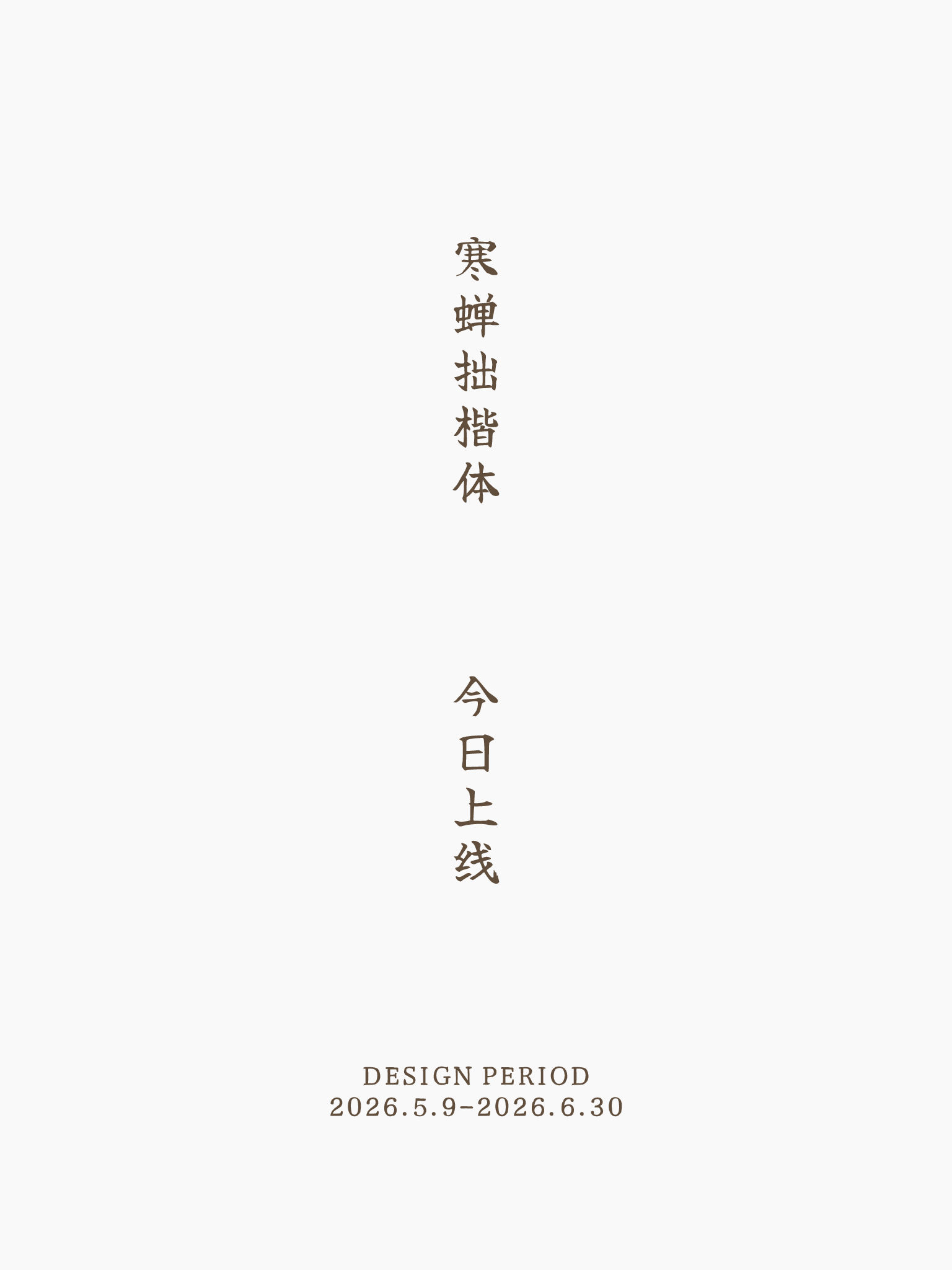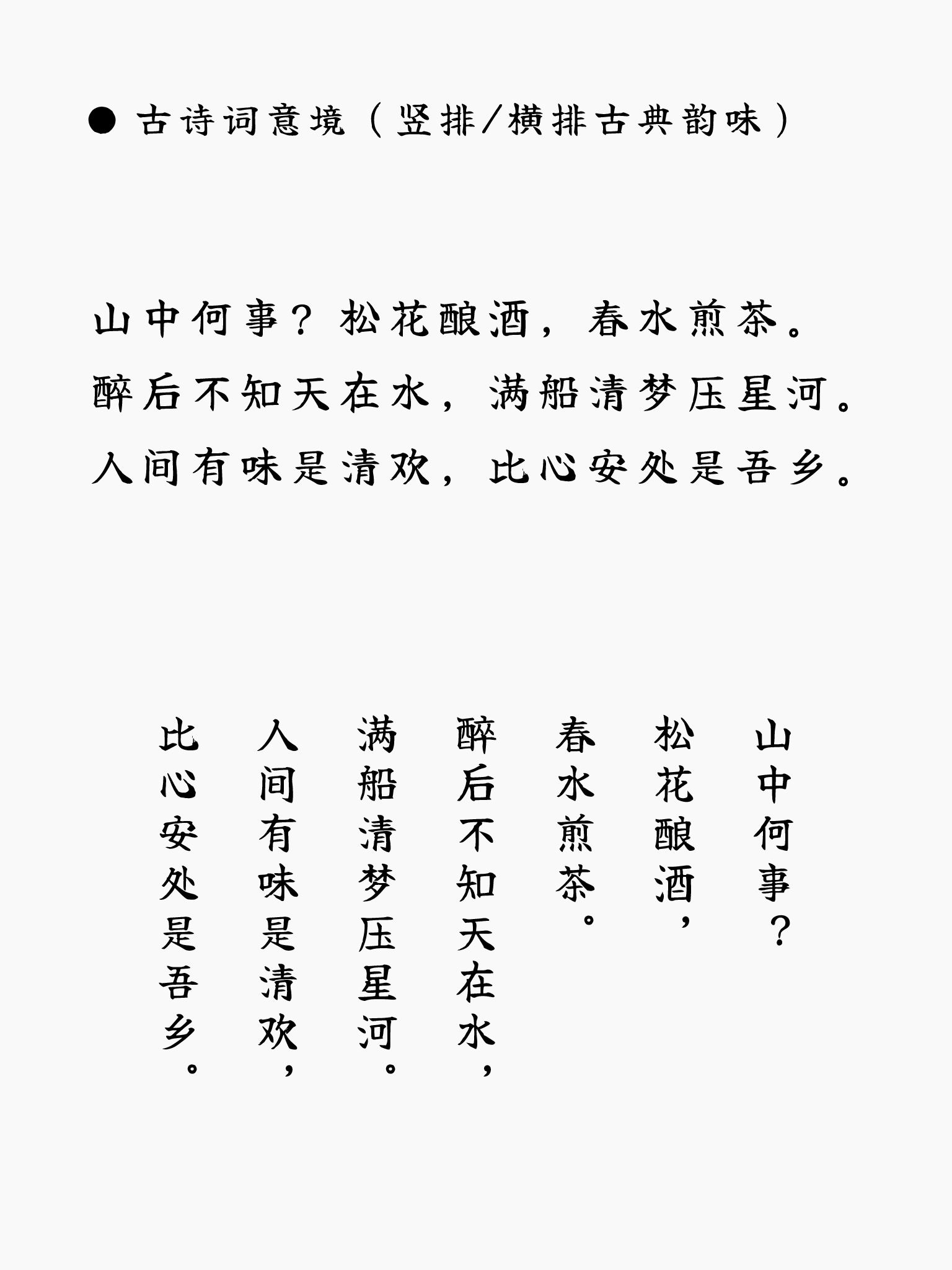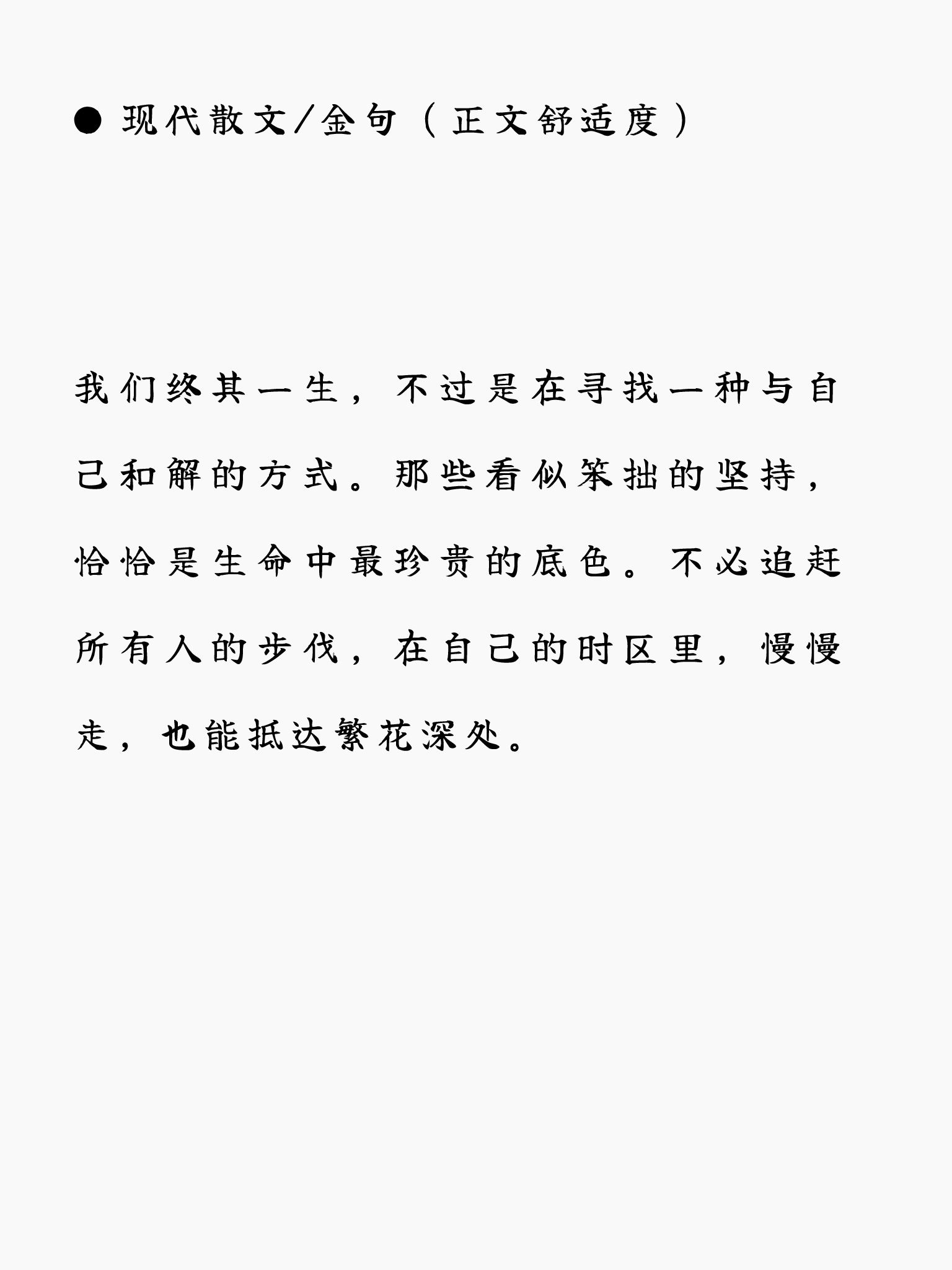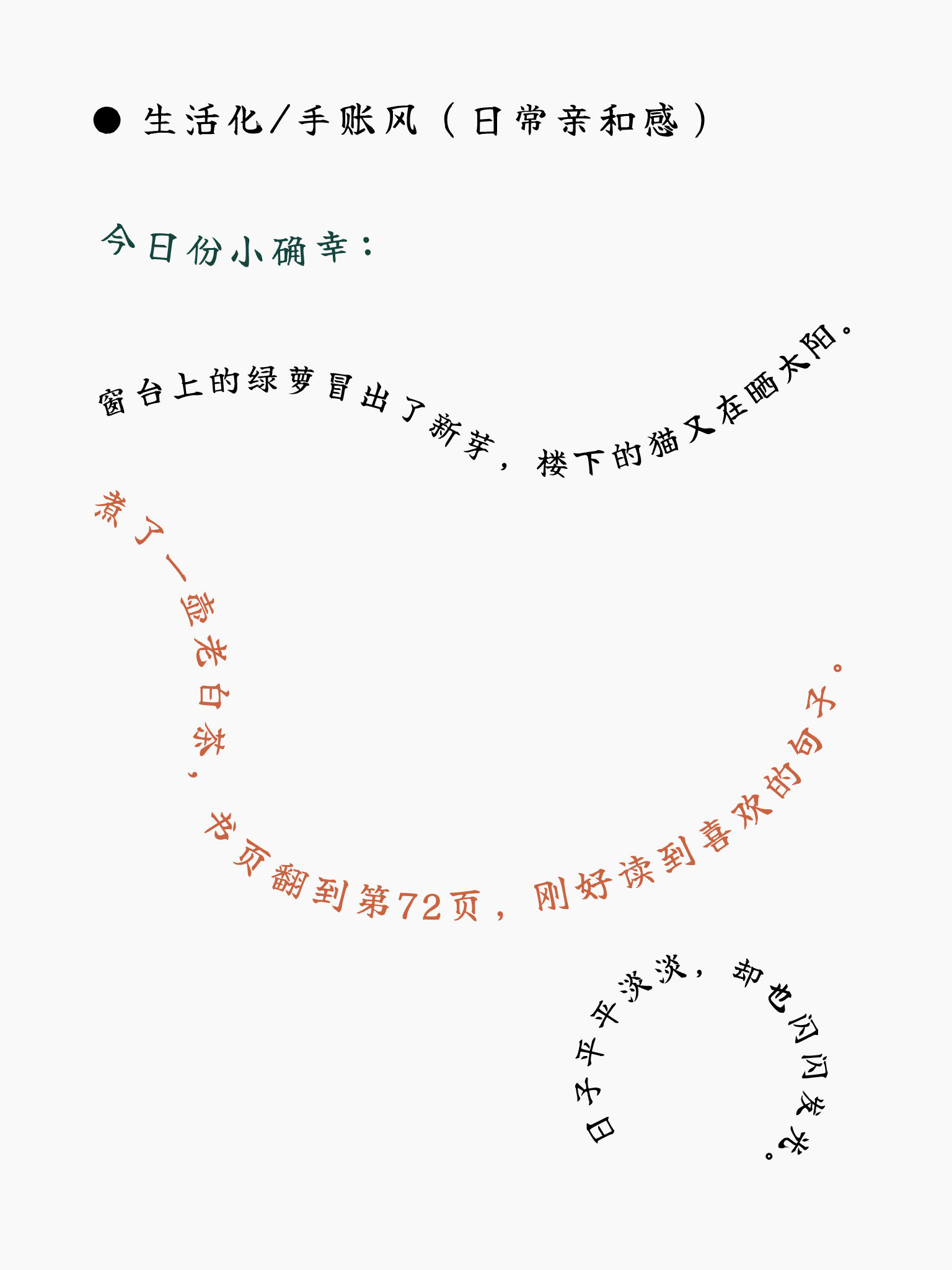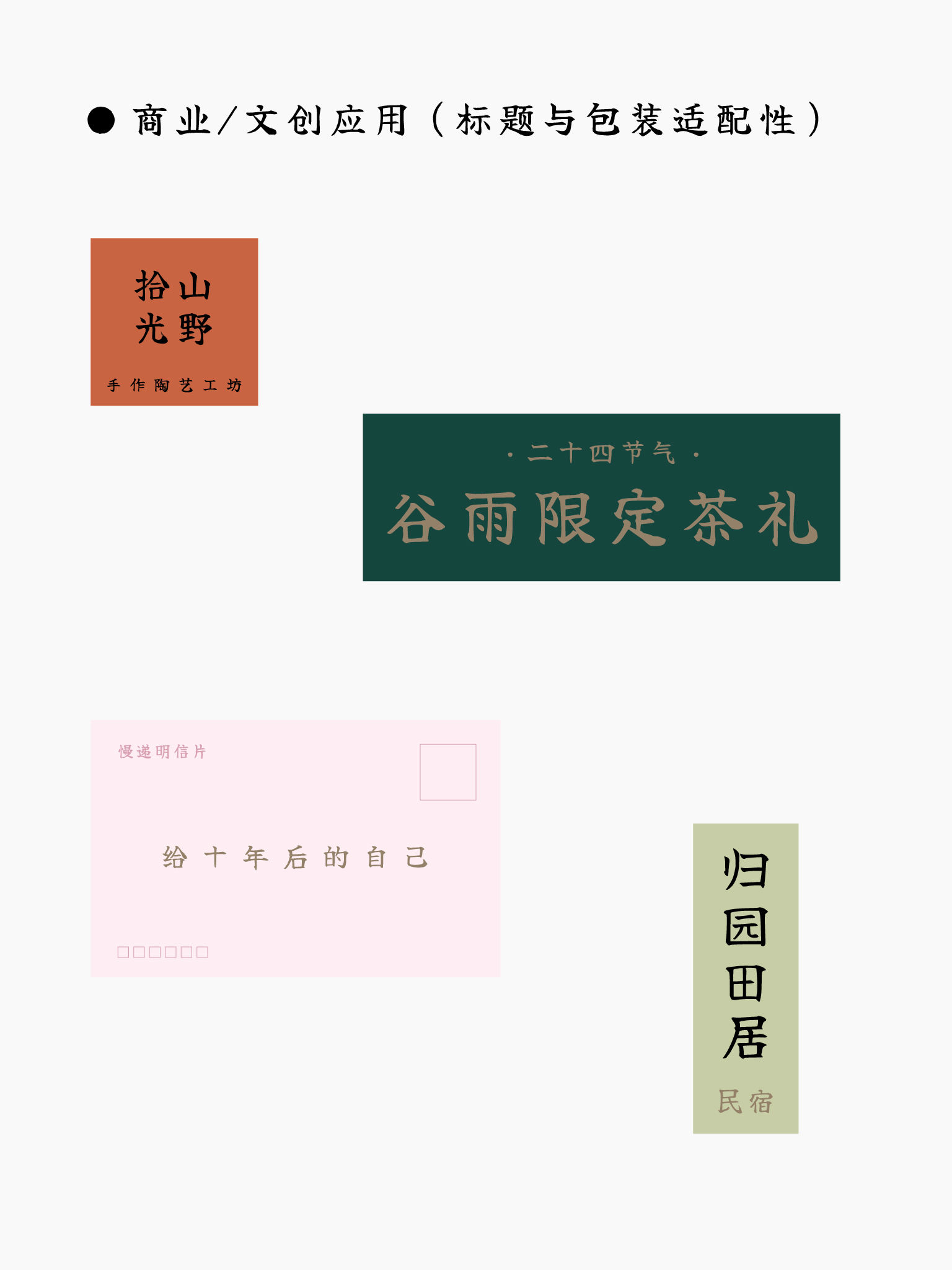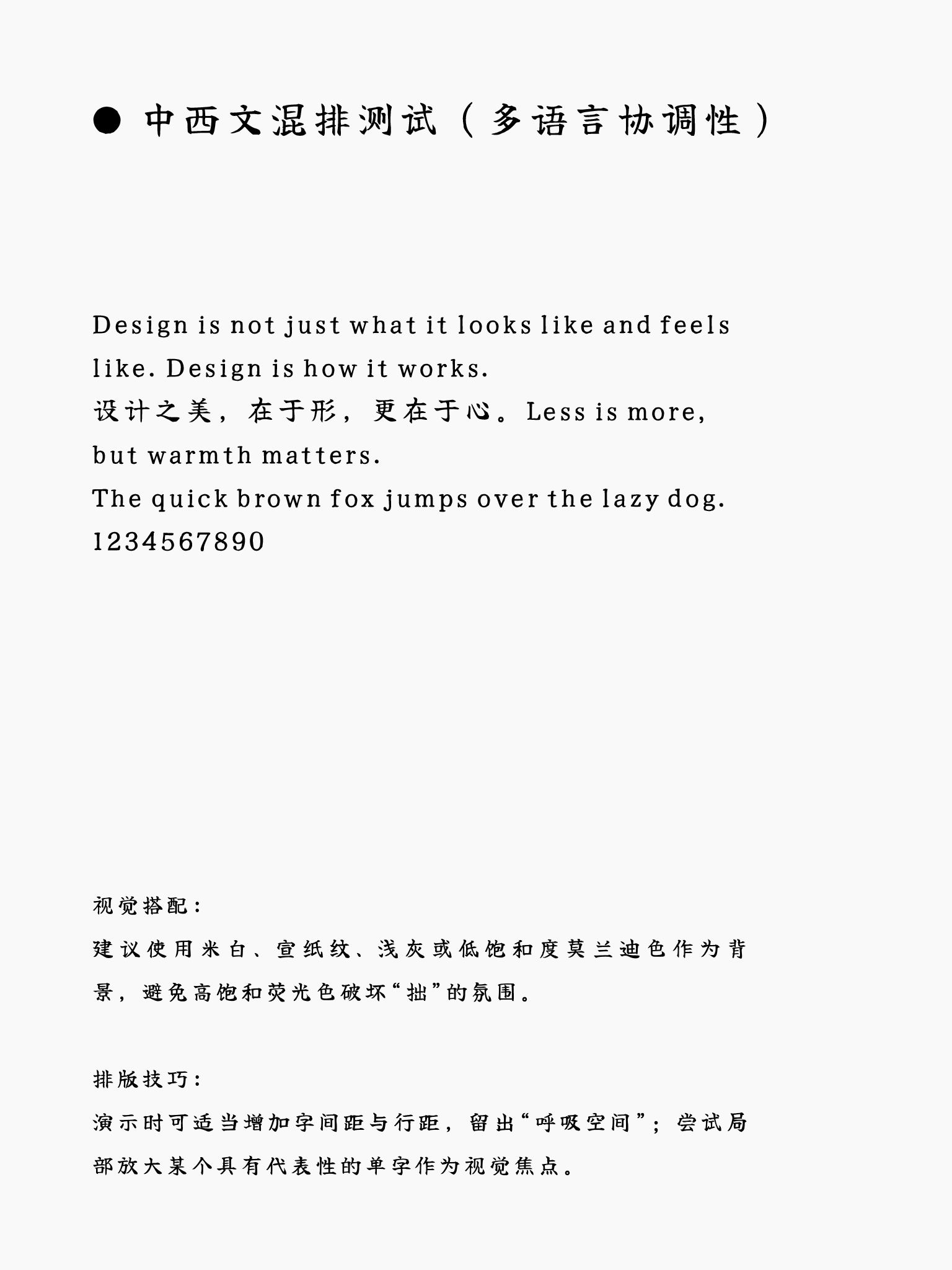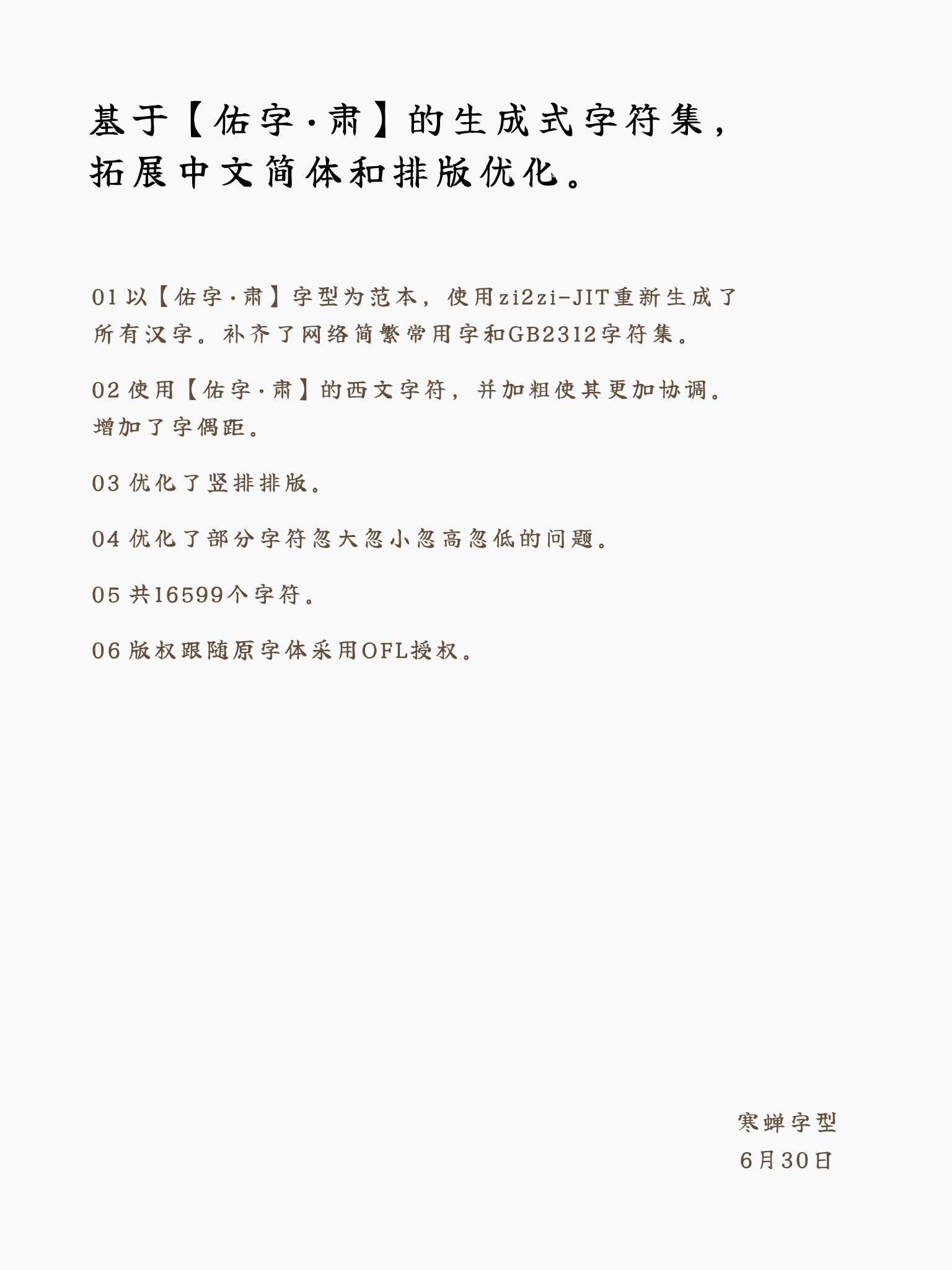
寒蝉拙楷体是一个基于机器学习技术开发的补简字体项目,通过zi2zi-JIT框架生成。该项目旨在扩展和补充特定字体在简体中文字符集方面的覆盖,同时保持其原有的书法风格与美学特征。zi2zi-JIT是一种基于深度学习的字体生成工具,能够有效学习原字体的笔画结构、形态特征以及整体排版风格,进而生成一致且高质量的补全字符。
原字体 Yuji Syuku(佑字 肃)是一款具有传统美感的日文字体,其设计融合了古典书法元素与现代排版需求,尤其在笔画细节和结构平衡上表现突出。为了保持风格的一致性,寒蝉拙楷体在生成过程中,参考了 SourceHanSerif(思源宋体)Regular 版本的骨架结构。思源宋体作为一款广泛使用的开源宋体字体,其笔画清晰、结构严谨,为寒蝉拙楷体提供了稳定的字形基础,确保新生成的简体字符在视觉协调性和可读性上与原有日文字符和谐统一。
通过这种方式,寒蝉拙楷体不仅丰富了原字体的字符支持范围,也为中文排版场景提供了更多样化的选择,尤其适用于需要兼顾传统风格与现代中文使用的出版、设计或数字内容领域。
寒蝉拙楷体今日上线,设计周期2026年5月9日至2026年6月30日。
此图呈现同一组古典诗词分别以横排和竖排的传统版式展示,包含完整诗句:“山中何事?松花酿酒,春水煎茶。醉后不知天在水,满船清梦压星河。人间有味是清欢,比心安处是吾乡。”
标题:现代散文/金句(正文舒适度)。我们终其一生,不过是在寻找一种与自己和解的方式。那些看似笨拙的坚持,恰恰是生命中最珍贵的底色。不必追赶所有人的步伐,在自己的时区里,慢慢走,也能抵达繁花深处。
生活化/手账风(日常亲和感)今日份小确幸:窗台上的绿萝冒出了新芽,楼下的猫又在晒太阳。煮了一壶老白茶,书页翻到第72页,刚好读到喜欢的句子。日子平平淡淡,却也闪闪发光。-刊刻Kntuk
商业/文创应用示例:陶艺工坊标志、谷雨茶礼标题、明信片设计、民宿品牌标题
中西文混排测试示例,包含设计引言与排版建议的多语言文字。
基于佑字·肃的生成式字符集公告:涵盖字体生成、简体扩展、排版优化、16599个字符及OFL授权。